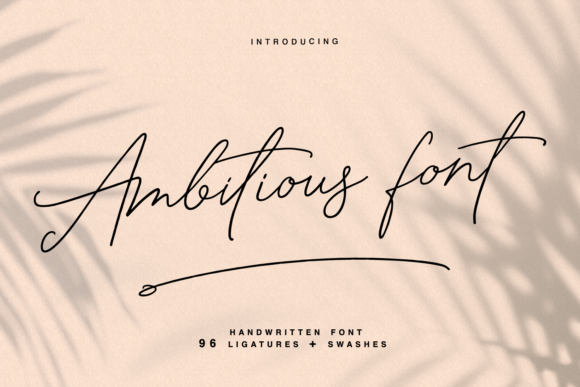
Ambitious
Trouver les bons éléments de conception peut être un défi, mais Ambitious propose une collection exceptionnelle qui rehausse instantanément votre travail.
Conçu avec précision, Ambitious offre des vecteurs nets, une typographie fluide et une licence commerciale pour une tranquillité d'esprit.
Que vous créiez des produits POD (impression à la demande), des invitations de mariage ou des visuels pour les réseaux sociaux, Ambitious est un choix idéal.